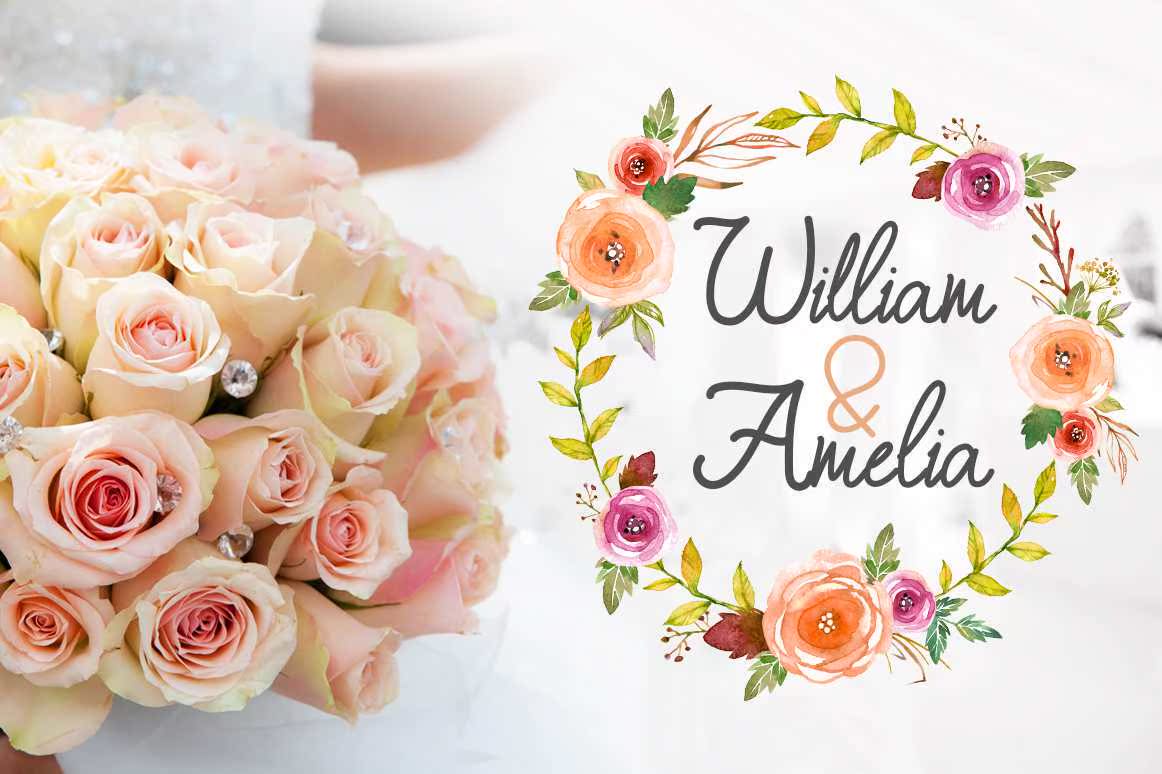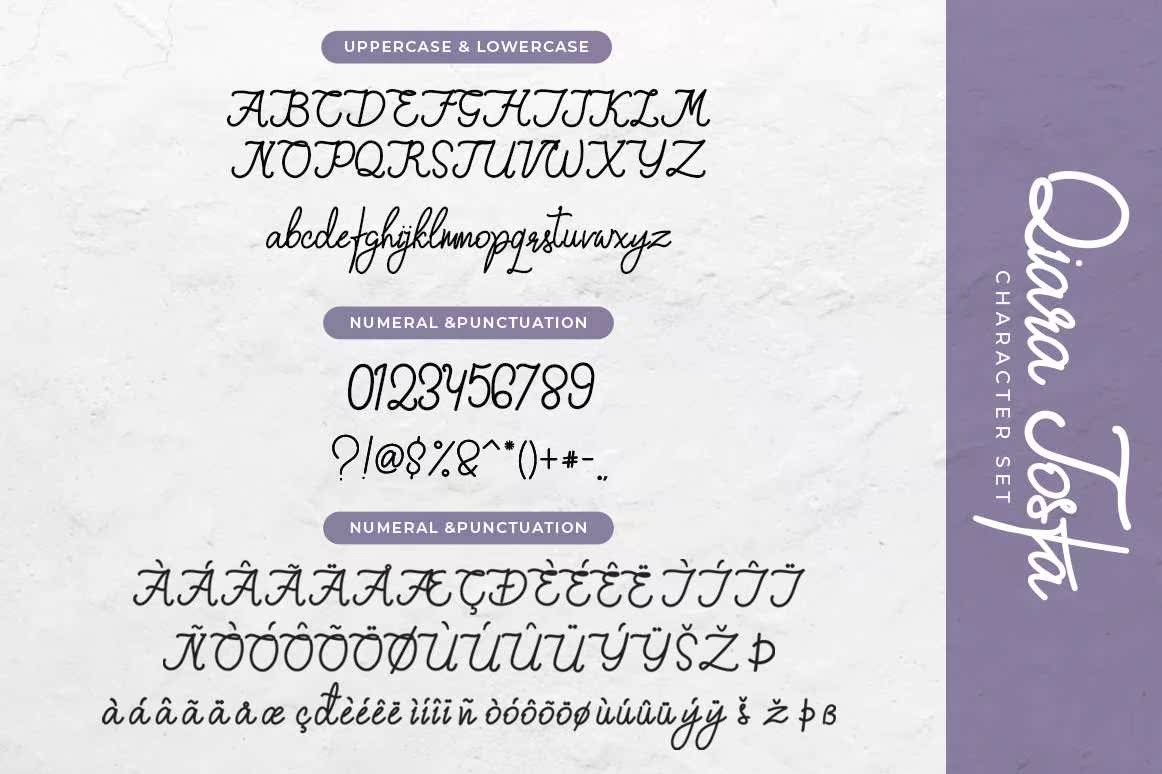
介绍QiaratosFaabeAbeautifulla和StyleshipHandrittenFont。此美丽的ScriptFont通过Legent、ClassandModernLook为您的最新项目提供了个性化触控。介绍QiaratosFaabeAbeautifulla和StyleshipHandrittenFont。此美丽的ScriptFont通过Legent、ClassandModernLook为您的最新项目提供了个性化触控。